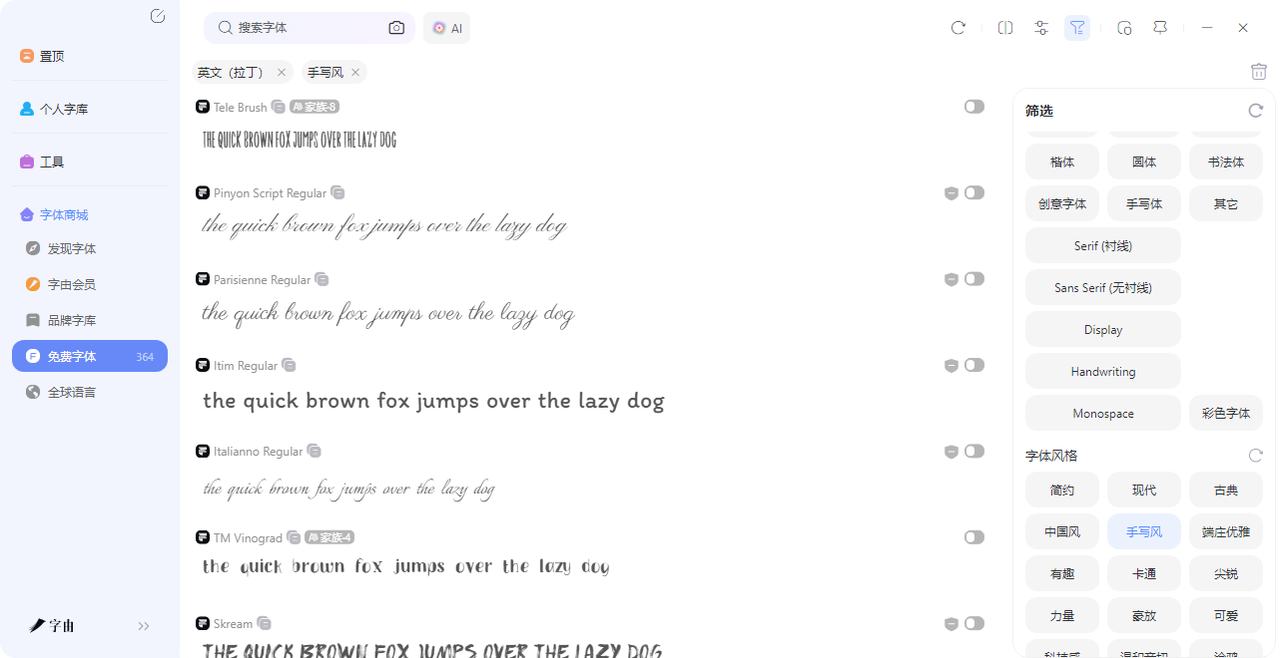
英文手写体字体网站推荐,让设计瞬间高级
做海报、写贺卡、搞 logo,总感觉差那么一点高级感?换款英文手写体试试,肯定有不一样的收获!但网上资源太杂,免费商用的不好找。那该怎么办呢?放心,今天我会推荐 5 个宝藏网站,从一键应用到 PS 的字由,到国外专门收录手写风格的字体库。每个都亲测过,附赠具体字体推荐和版权提醒。看完这篇,你的字体库肯定会新添很多新内容。
如果你经常在 PS、AI、Figma 里做图,应该听说过字由。它是一个集字体库、字体管理、AI 工具于一体的客户端,目前收录超过 10500 款字体,其中 3585 款免费商用(目前最新,还会再持续上新)。注册用户超过 2000 万,背后是上市公司全资品牌。
这次我们来专门聊它的英文手写体资源。接下来我会教大家如何在字由里寻找免费的英文手写体字体。
打开字由客户端,在筛选栏里选择“英文(拉丁)”+“手写风”,立马能看到几百款相关字体。我数了一下,光是免费标签下就有 364 款。这个数量比很多专门的英文字体站还多。随便翻几款就能发现好东西。比如:
- Pacifico:这是一款非常经典的流畅手写风格,笔触圆润,带一点复古感,适合用在餐饮品牌、咖啡海报上。
- Great Vibes:属于优雅花体,连笔效果华丽,做邀请函、婚礼请柬的时候特别出效果。
- Parisienne Regular :也是类似风格,但笔画更纤细,适合搭配简约排版。
- Italianno Regular:它的倾斜角度比较大,像用钢笔快速写出来的,用在个人签名或者艺术字标题上很有张力。
- Skream:这款稍微带一点涂鸦感,笔触粗犷,适合街头风格的海报。
字由最方便的地方不是“找字体”,而是“用字体”。你不需要下载安装,也不用重启软件。在客户端里点一下字体旁边的“对号”图标,它就会自动激活到你的 PS、AI 或者 Figma 里。我上次帮朋友做一张英文手写风格的 album cover,选了 Grand Hotel Regular,一键激活,直接在 Photoshop 的文字工具栏里就能找到,全程不到 10 秒。
2、English Font
English Font,它的首页有个 Most Popular Font 列表,直接按下载量和浏览量排序。对于不知道选哪款英文手写体的人来说,这个排行榜很实用,这个网站大部分字体是个人免费使用,商用的话需要点进具体字体页面看授权说明。很多热门字体标注的是“Free for personal use”,商用最好联系作者或者买授权。不要看下载量大就默认免费商用。这个网站的左侧有非常细的标签筛选,比如 Brush(笔刷体)、Chalk Crayon(粉笔蜡笔)、Graffiti(涂鸦)、Old English(古英语花体)等等。如果你想要那种复古的英文手写体,直接点 Old English,出来的都是哥特式手写风格。
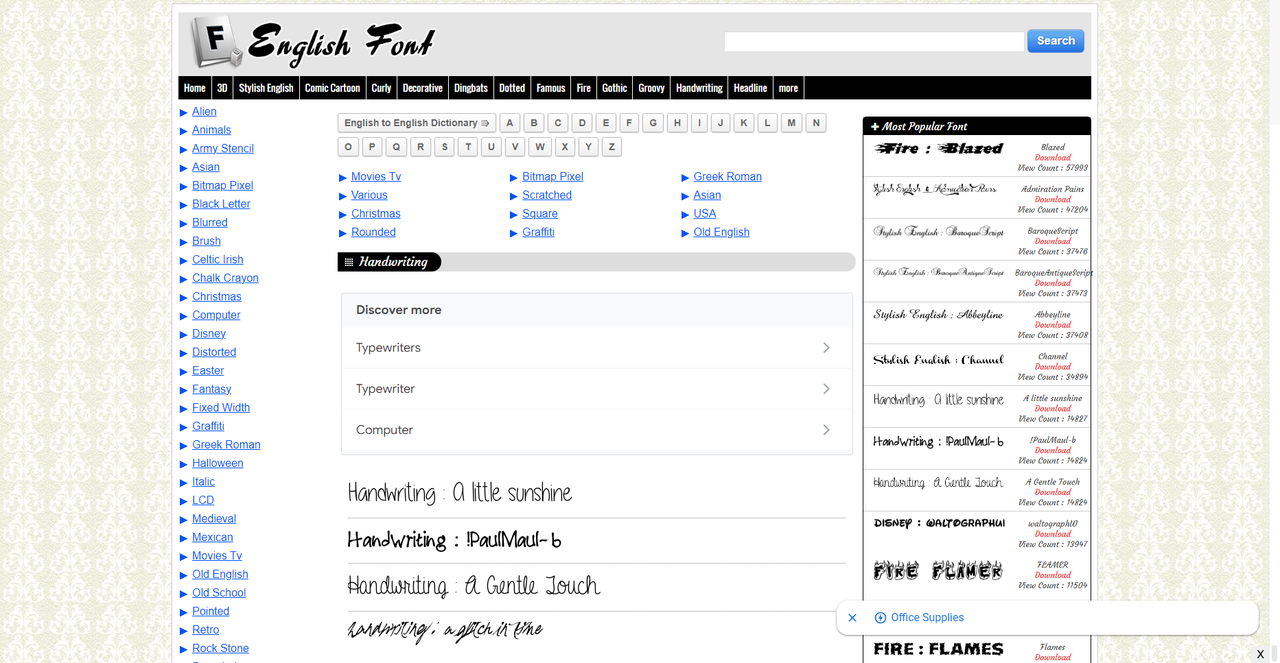
3、All Fonts
第二个网站叫 All Fonts。它专门整理了一篇文章:66 Best Free Handwritten Fonts。最良心的是,页面顶部明确写了“These fonts come from Google Fonts or web-safe system fonts, are completely free for commercial use, and do not require any copyright license or attribution.”——全部来自 Google Fonts 或系统自带字体,完全免费商用,不需要署名。这对于做商业项目的设计师来说简直是福音。你不用担心版权问题,直接下载或者用 CSS 调用都行。因为所有字体都来自 Google Fonts,你不需要下载安装。在 Google Fonts 官网上搜索字体名字,点击 “Get font” 就能获得嵌入代码,直接用在网页上。做平面设计的话,下载字体文件再安装到本地就行。
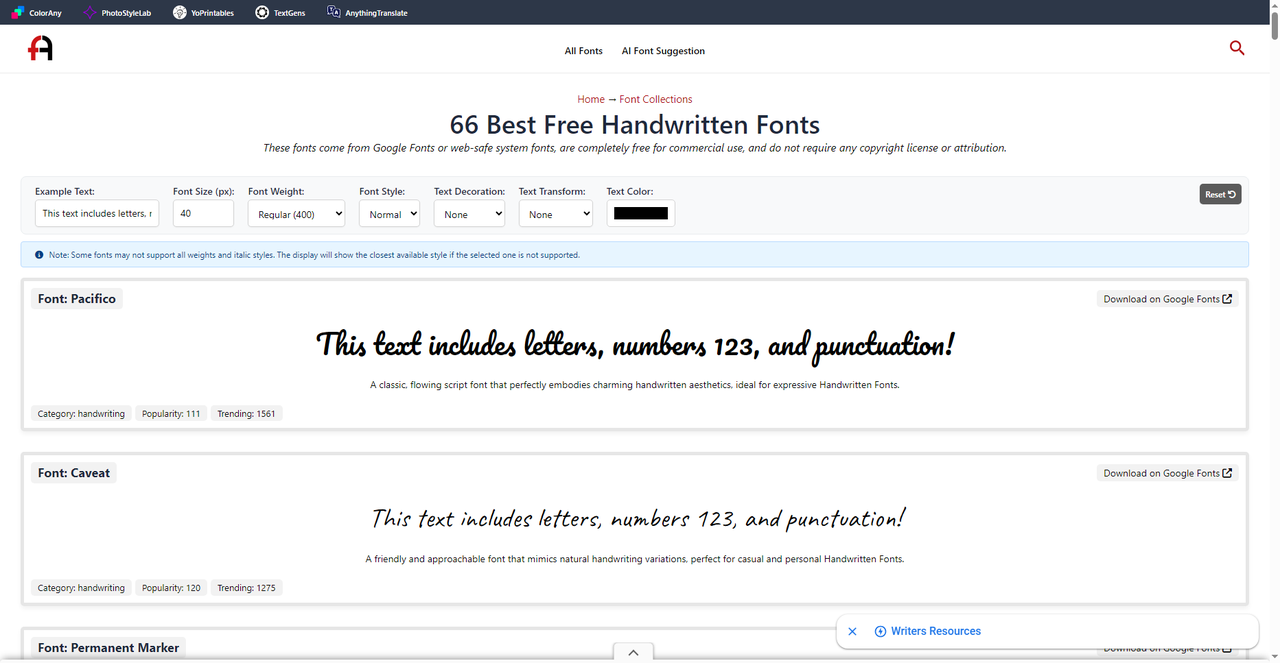
4、Handwriting Fonts
第三个网站叫 Handwriting Fonts。它的设计比较简洁,一进来就看到几个热门推荐。最显眼的是 Tomatoes by Billy Argel Fonts,显示“1.1 million downloads”——110 万下载量。这款字体叫 Tomatoes,风格像用番茄酱瓶子写出来的,笔画有点歪歪扭扭,但很有手作感,适合做食品包装或者复古海报。这个网站的筛选功能也比较实用。顶部有 Type your own text... 输入框,你可以打一段文字,预览每种字体的实际效果。右边的 Commercial-use 和 Popular 按钮,可以快速过滤出免费商用和高人气字体。页面标注了“Commercial-use”标签的才能商用。像 Tomatoes 虽然下载量巨大,但点进去要看作者的具体授权。很多独立字体作者采用“个人免费 + 商用付费”的模式,不要默认免费商用。
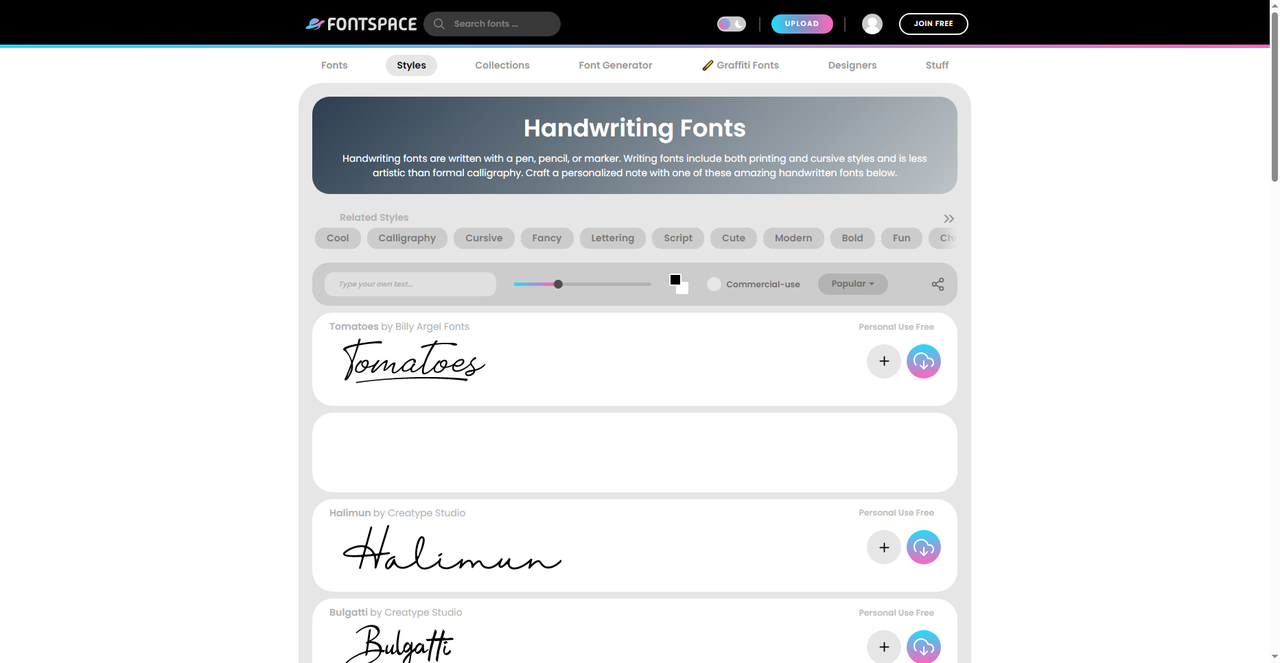
5、Adobe Fonts